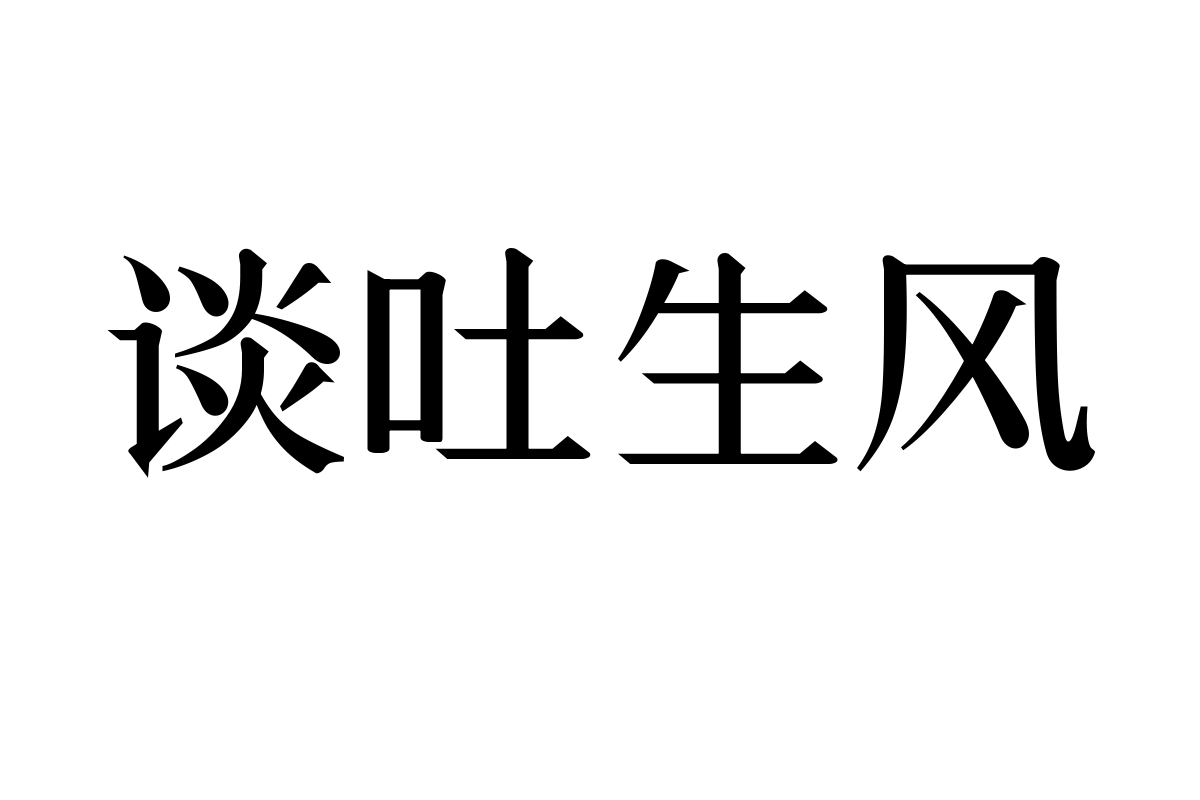
三极萧宋简体中粗字体是一种常见的中文字体,主要用于印刷和排版。这种字体的特点是笔画粗细适中,字形结构稳定,易于阅读和识别。它广泛应用于报纸、杂志、书籍、广告、商标等各种出版物的排版设计中。
三极萧宋简体中粗字体的特点如下:
1. 笔画粗细适中:这种字体的笔画粗细适中,既不过于细长也不过于粗壮,使得文字看起来既清晰又美观。
2. 字形结构稳定:三极萧宋简体中粗字体的字形结构稳定,字形端正,没有明显的倾斜或变形,使得文字看起来整齐有序。
3. 易于阅读和识别:由于笔画粗细适中且字形结构稳定,三极萧宋简体中粗字体的文字在长时间阅读或打印过程中不易产生疲劳感,易于阅读和识别。
4. 适用范围广泛:三极萧宋简体中粗字体适用于各种印刷和排版场景,包括报纸、杂志、书籍、广告、商标等。
总之,三极萧宋简体中粗字体是一种实用的中文字体,广泛应用于各种出版物的排版设计中。